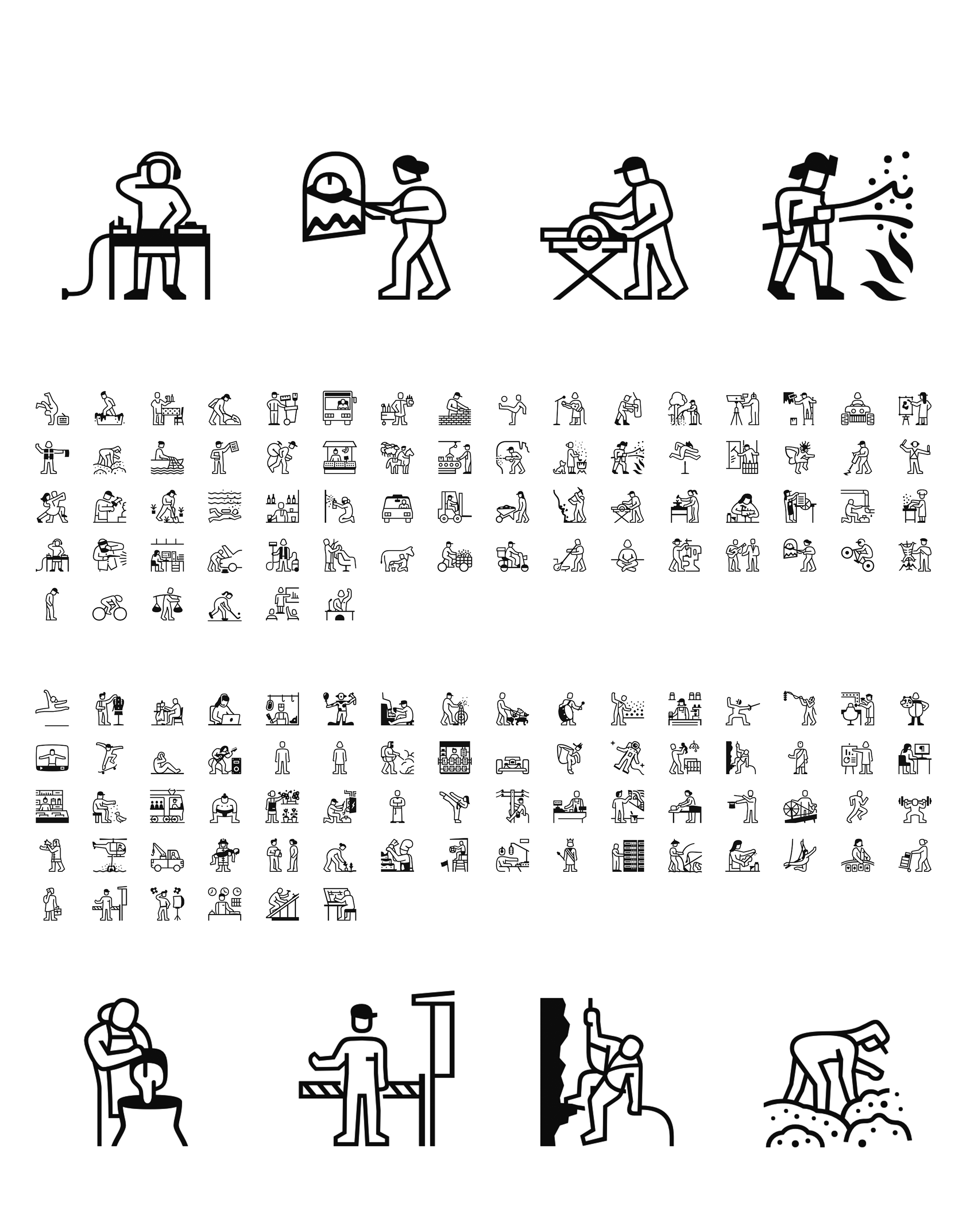
| Descripción | Vivaceta es un conjunto de pictogramas y símbolos que representan diferentes actividades humanas. Vivaceta se ha planificado para una expansión constante: cada fuente contiene 70 glifos, etiquetados en español: Vivaceta UNO, DOS, TRES, etc. Vivaceta muestra el mundo de los trabajos y las labores, en áreas tan diversas como el deporte, el transporte, la gastronomía, el arte, la construcción, etc. En estos conjuntos pictográficos, los glifos comparten el espacio como expresión de igualdad e integración: cada actividad tiene un valor. |
| Familia(s) | Vivaceta-UNO, Vivaceta-DOS, Vivaceta-TRES |
| Lenguajes | Iconográfico |